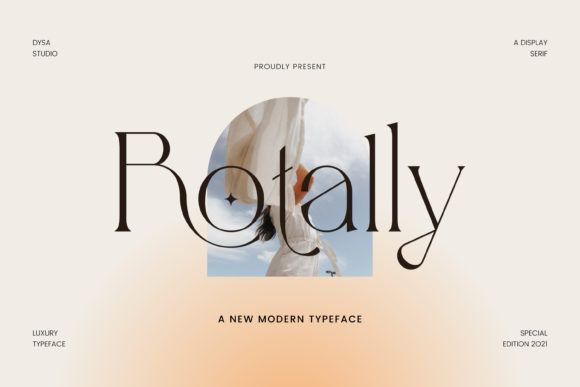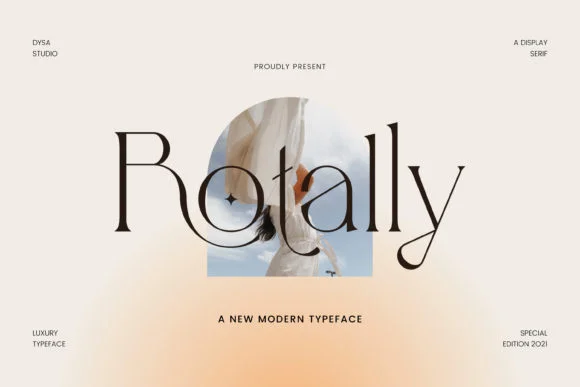
Название: Rotally Font (2021)
Rotally - элегантный и тонкий шрифт с засечками.
Он добавит роскошную искру в любой дизайнерский проект, который вы захотите создать!
Влюбитесь в его невероятно универсальный стиль и используйте его для создания эффектных дизайнов!
Название: Rotally Font (2021)
Rotally - элегантный и тонкий шрифт с засечками.
Он добавит роскошную искру в любой дизайнерский проект, который вы захотите создать!
Влюбитесь в его невероятно универсальный стиль и используйте его для создания эффектных дизайнов!